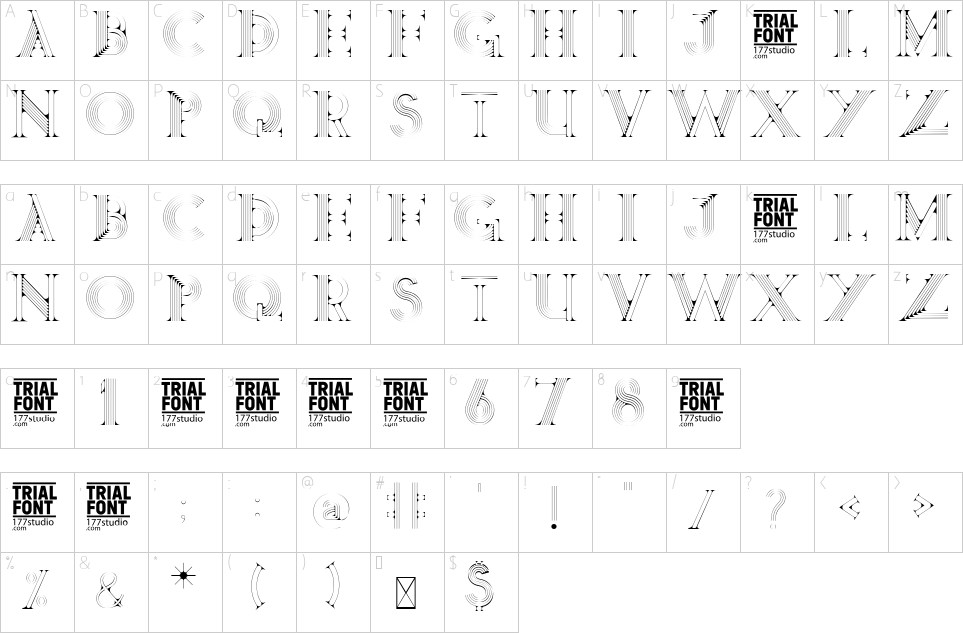
A ‘Genre Line’ é uma fonte leve e elegante que combina facilmente com diversos estilos de design. Com seu design minimalista, essa fonte se destaca como uma opção versátil para qualquer projeto visual. Ela foi criada por 177Studio.com e já está disponível para quem deseja incorporá-la em suas produções digitais, tanto no Windows quanto na Mac. A ‘Genre Line’ tem sido um recurso frequentemente solicitado pela comunidade de designers online, tendo sido baixada centenas de vezes. Se você está procurando por uma fonte que seja sofisticada e prática para o seu próximo projeto, a ‘Genre Line’ pode ser justamente aquilo em que você precisa.